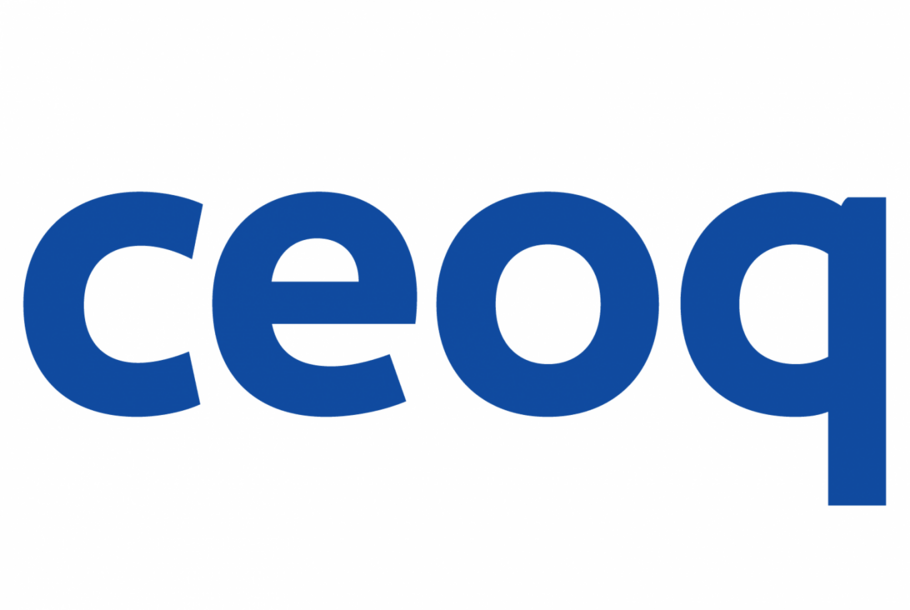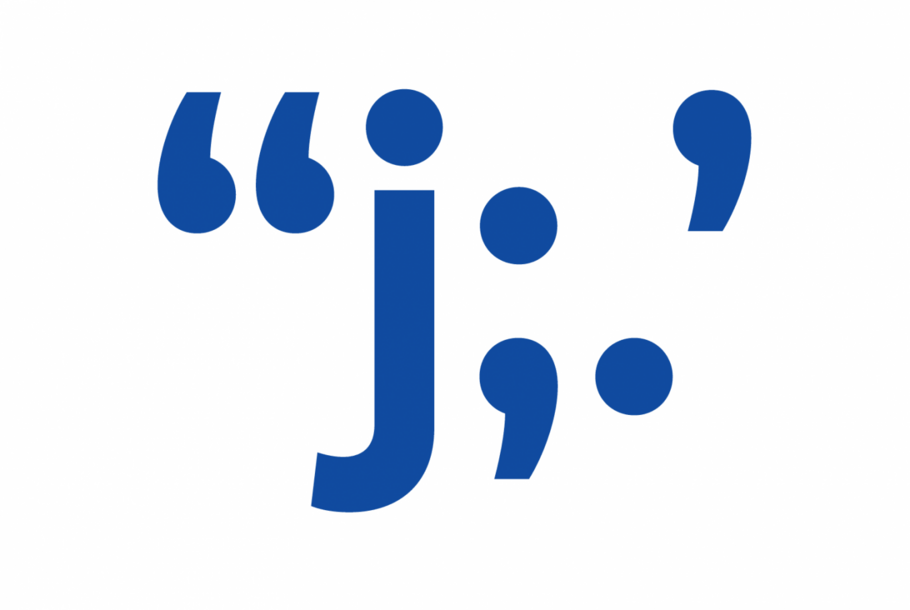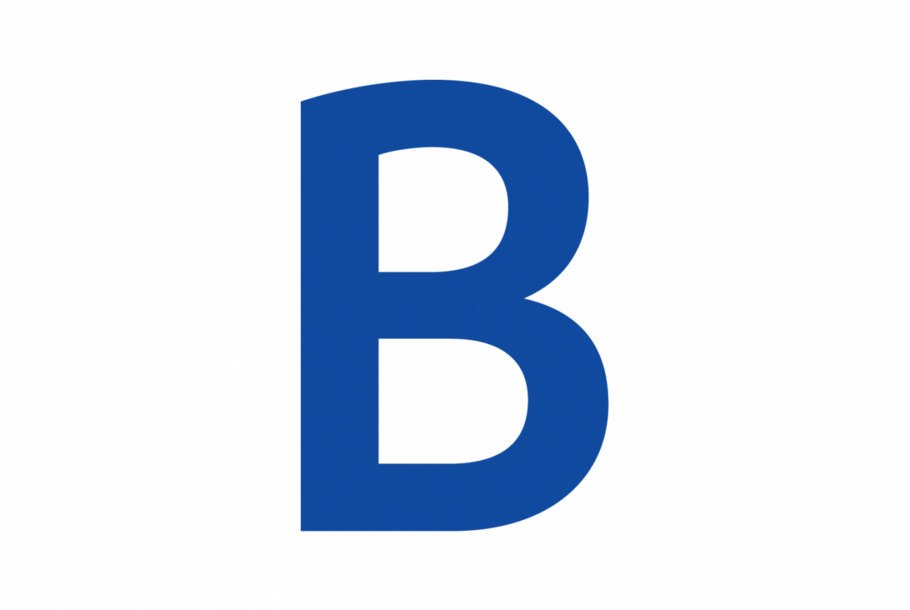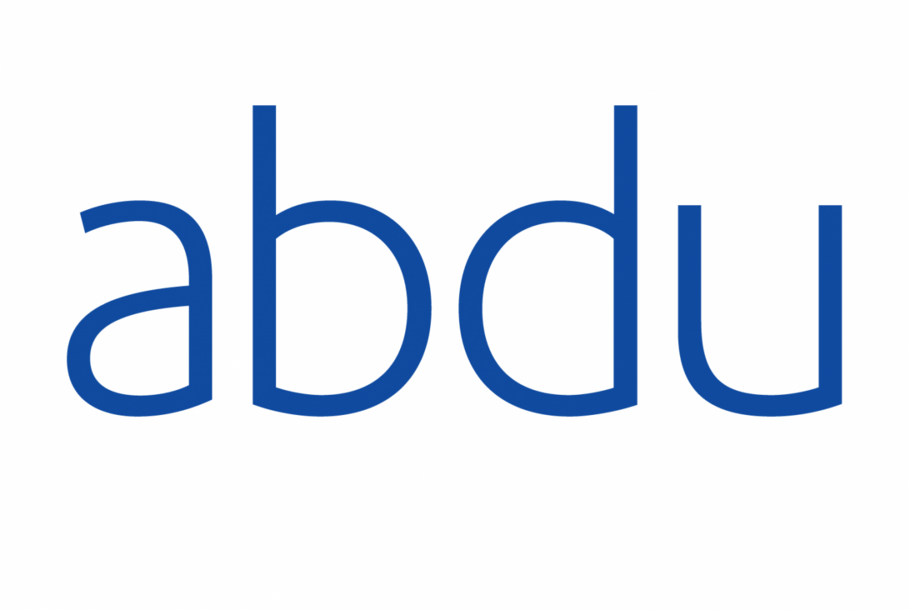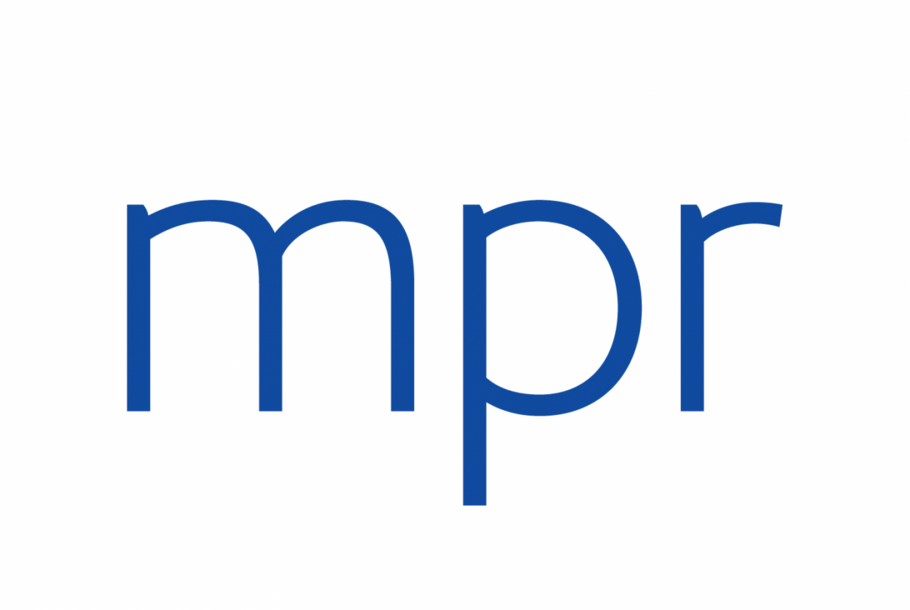
サウスウエスト航空のための、心を込めた書体.
MonotypeとLippincottはサウスウエスト航空と緊密に協力し、この愛される航空会社ブランドのために、新たなアイデンティティの中心となるタイポグラフィの声を生み出しました。
サウスウエスト航空は、約半世紀にわたり、顧客との真摯で感情的な繋がりをブランド体験の真髄とするビジネス哲学を磨き続けてきました。そして2014年、同社はその人間味あふれる価値観をより前面に打ち出すべく、ブランドの刷新を発表しました。それは、機体塗装、空港、デジタルチャネルを含む全面的な見直しであり、斬新なビジュアルアイデンティティの導入でもありました。機体からピーナッツのパッケージに至るまで、新しいブランディングは、サウスウエスト航空の自信と誠実さを、現代的な表現で伝えるものとなっています。
「私たちの鼓動はこれまで以上に強く、健やかに響いています。それは、社員一人ひとりの温かさ、思いやり、そして笑顔のおかげです」と、サウスウエスト航空の会長兼社長であり最高経営責任者(CEO)のGary Kellyは語ります。「機体に描かれたハート、そして新しいデザインの中にあるハートは、私たちが将来を見据える中で、基本的な価値観に忠実であり続けるという決意を象徴しています」
Southwest’s full brand refresh covered livery, airports, digital channels and a fresh new visual identity.
新しいアイデンティティの要となったのは、サウスウエスト航空社内のカルチャー——人間味や個人とのふれあいを大切にする文化——を視覚的にわかりやすく表現することでした。とりわけ、競合がひしめき、消費者の目も厳しさを増す現在の市場において、こうした価値を誠実に表現することがより一層求められています。
その実現に向けて、サウスウエスト航空はLippincottと提携し、同社が掲げる「ヒューマン・エラ・ブランディング(Human Era Branding)」の哲学に基づいた新たなアイデンティティを創り出しました。この哲学は、ブランドと消費者の間に、シンプルで誠実なコミュニケーションを築くことを重視しています。
Lippincottのシニアパートナー、Rodney Abbottは次のように説明しています。「ヒューマン・エラ・ブランディングは消費者の心に訴えかけます。ときに弱さを見せることもあれば、力強く、ユーモラスだったり真面目だったりすることもある。いずれの場合でも、その感情表現は本物であり、企業のDNAや存在意義に根ざしているといえます」
もちろん、言葉は最も強力なコミュニケーション手段の一つです。書体はストーリーテリングを支えるものであり、ブランドの個性を視覚的に体現することができます。このことを念頭に置き、Lippincottとサウスウエスト航空はMonotypeと緊密に協力して、ブランド専用のカスタム書体「Southwest Sans」を開発しました。このオリジナル書体は、Dan RhatiganとMonotypeのタイプデザイナーであるJim Fordによって制作され、サウスウエスト航空の個性を体現すると同時に、その「声」に多様で新たな表現を与えるよう設計されています。ブランドとして、消費者との真のつながりを築くためには、どのような場面でも独自のトーンを明確に伝える必要があります。そのため、書体はサウスウエスト航空の声を伝える上で重要な役割を担う必要がありました。
Southwest Sans typeface was inspired by the core symbol of Southwest’s identity- the heart.
サウスウエスト航空のアイデンティティにおける象徴的な存在——それは「ハート」です。ロゴタイプは、そのモチーフとの調和を意識して再設計されました。そのデザインの特徴は、書体全体のビジュアルを形づくる指針として、Southwest Sansに活かされています。方向転換を示す箇所は、シンプルな鋭いポイントで表現され、ラインは優しくアーチを描きながら、丸みのある曲線へとつながります。一部の字形ではステム(縦画)が構造的役割を果たし、コピー全体を読みやすくしています。大きな円は、親しみやすさや若々しい印象を与え、ベースラインに沿った丸みを帯びたスパー(突起)や強調されたボウル(ふくらみ)は、文字に遊び心のある表情を加えています。このバランスを取るために、書体全体では幾何学的な比率を採用し、太さのコントラストを最小限に抑えることで、モダンで親しみやすい印象を与えています。
The Southwest Sans typeface can be seen on everything from planes to peanut packaging.
ご想像の通り、この書体はサウスウエスト航空のブランド刷新において中心的な役割を果たしており、現在では機体の塗装、空港のサイン、Webサイトはもちろん、ピーナッツのパッケージやドリンククーポン、カクテルナプキンに至るまで、実に多様なブランド表現に使用されています。Southwest Sansは、どんなに小さな文字、あるいは大きなサイズでもブランドの声を的確に伝えられるよう設計されており、すべての言葉に意味を持たせ、確かな存在感をもたらします。
「この大胆な新しいビジュアルは、私たちの従業員の心と、お客様へのブランドとしての約束を表現しています」と、サウスウエスト航空のチーフ・マーケティングオフィサー、Kevin Kroneは述べます。「LippincottとMonotypeと共にカスタム書体を開発したことで、すべての文字に私たちのユニークな個性、声、ビジュアルアイデンティティを込めることが可能になりました」
Dan Rhatigan (left) and Rodney Abbott (right) reviewing the Southwest Sans typeface.
同社は財務面でも業界屈指の実績を誇ります。41年間連続で黒字を達成し、最近では「エアライン・オブ・ザ・イヤー」および「2014年のトップ投資先」に選ばれました。しかし、ビジネスでの成功に甘んじることなく、サウスウエスト航空は「ほんの少しの思いやりが、大きな価値を生む」という哲学を貫き、世界に示してきました。
今日では、旅行者は常に新しいブランドや選択肢にさらされています。その中で、書体を通して親しみやすく人間味のあるトーンで消費者に語りかけることは、ブランドを形づくる上でますます重要な役割を果たしています。